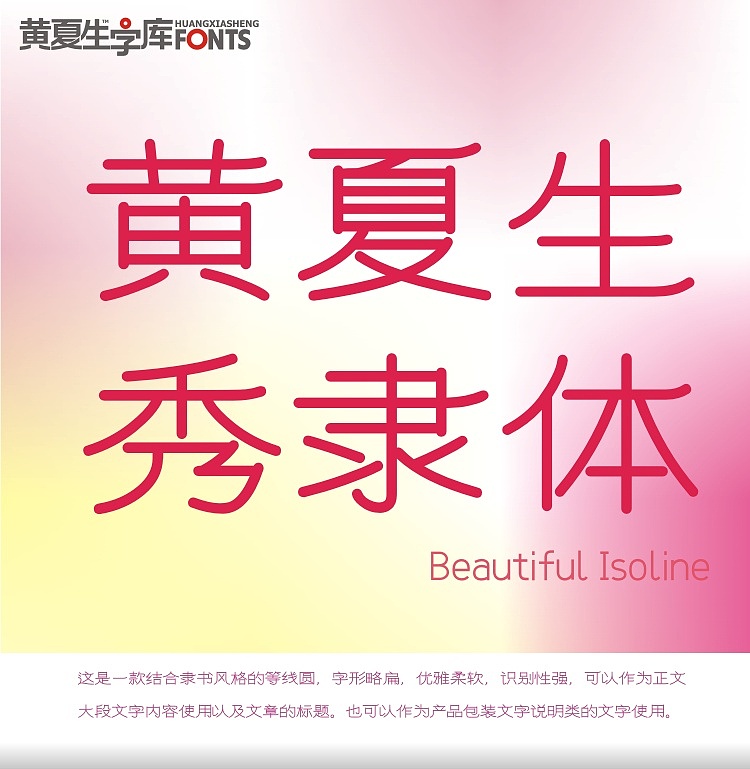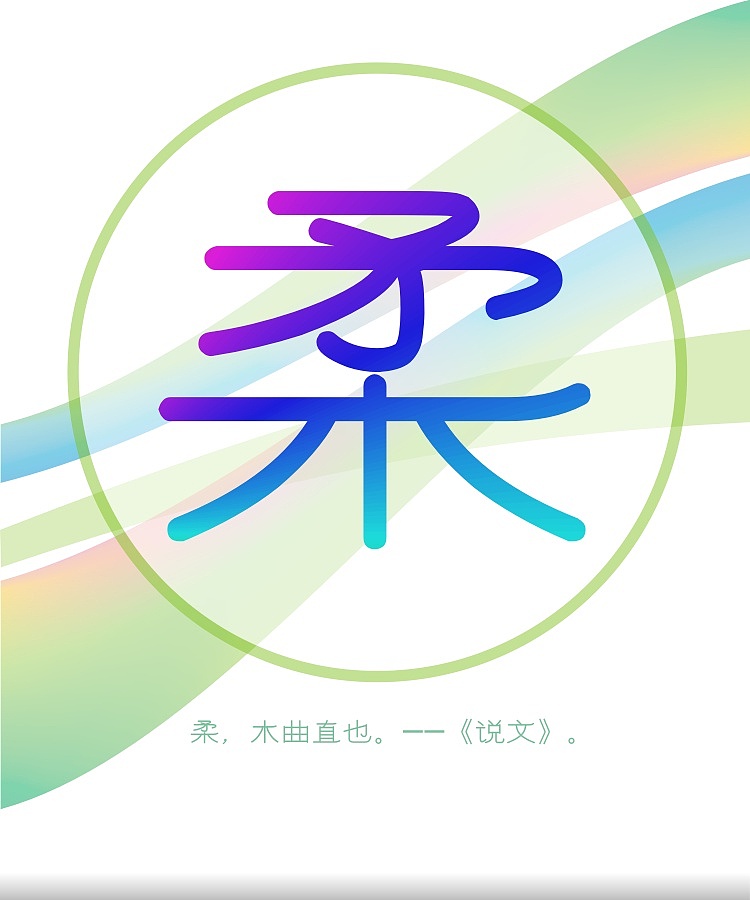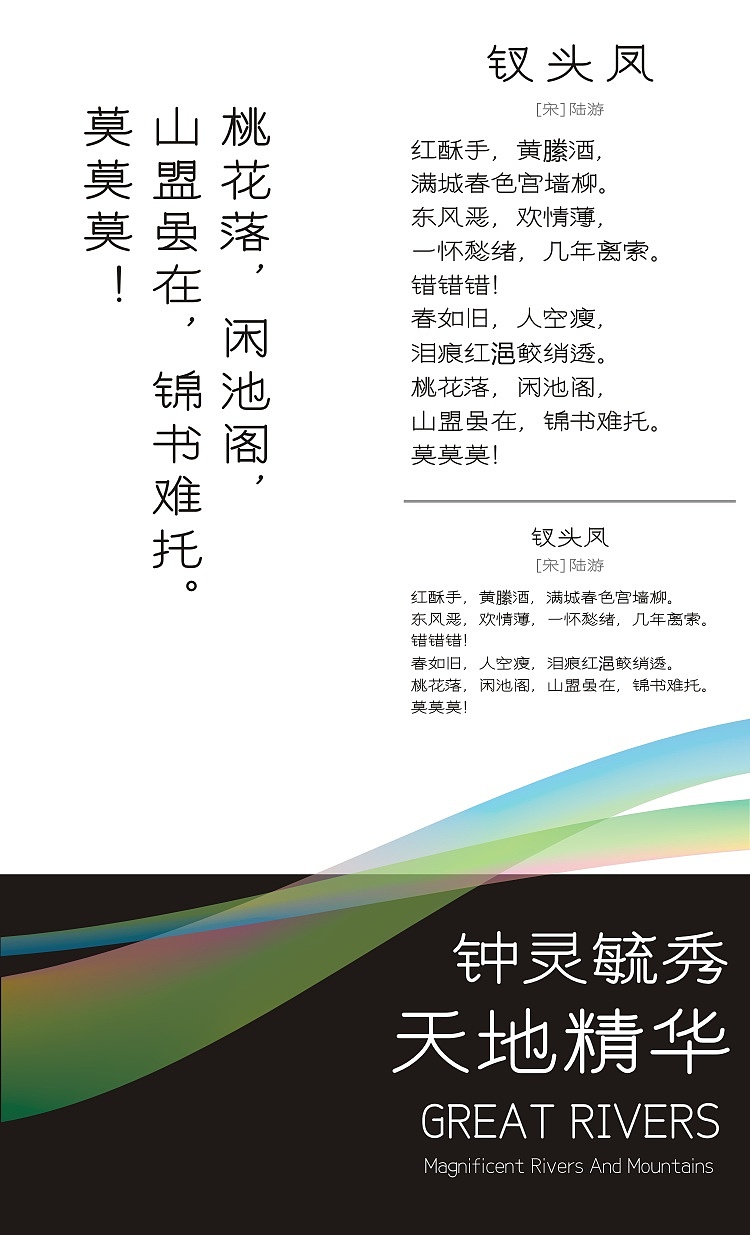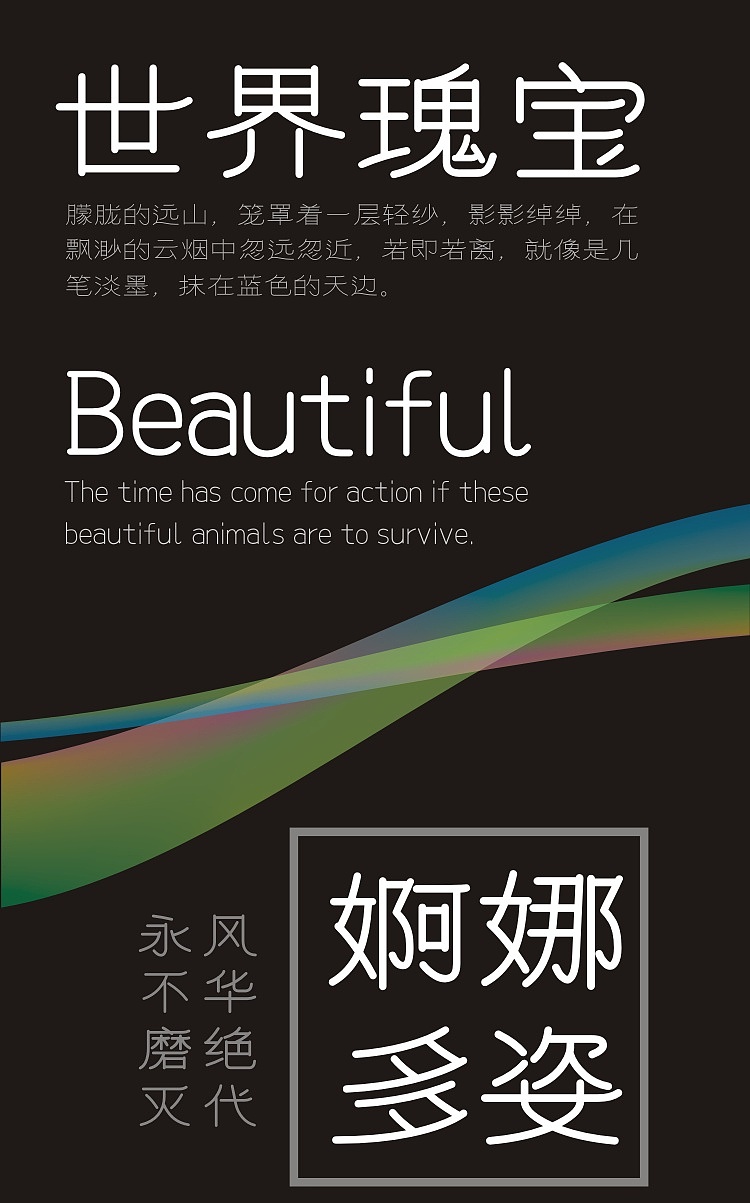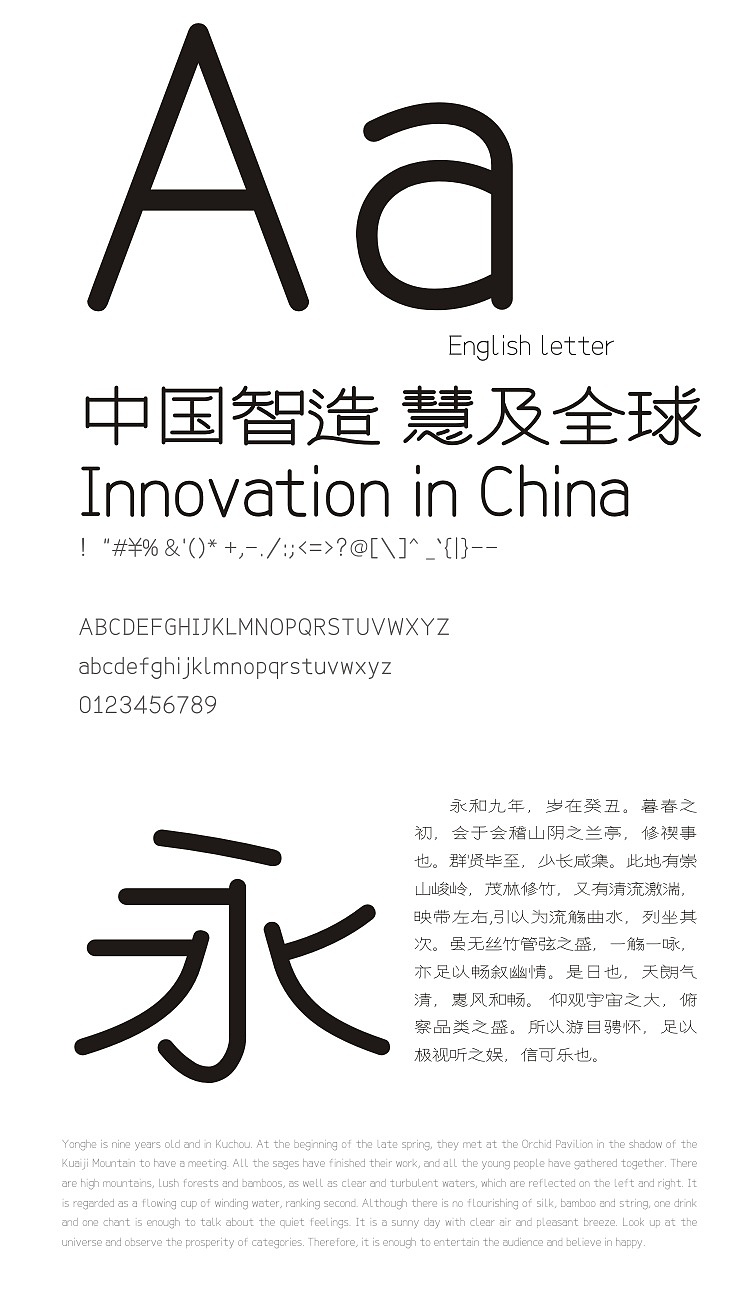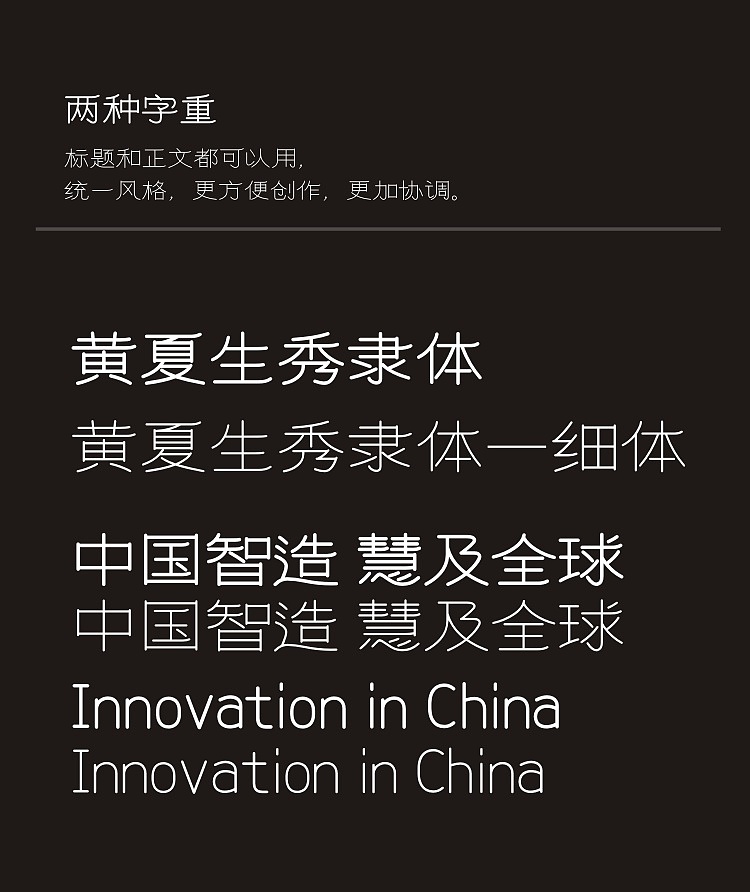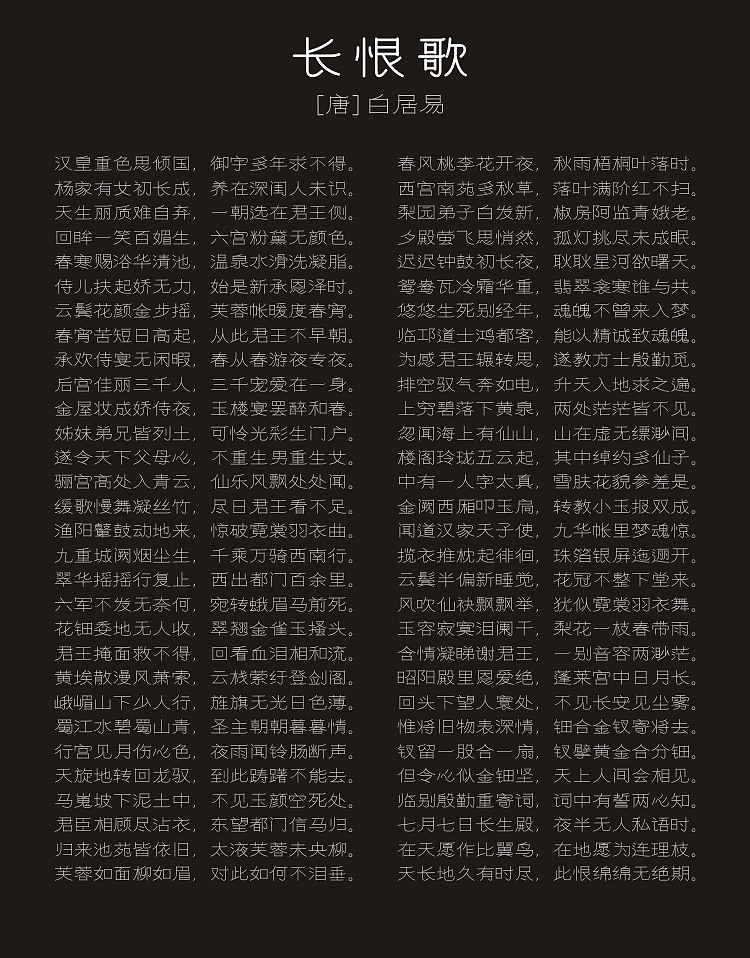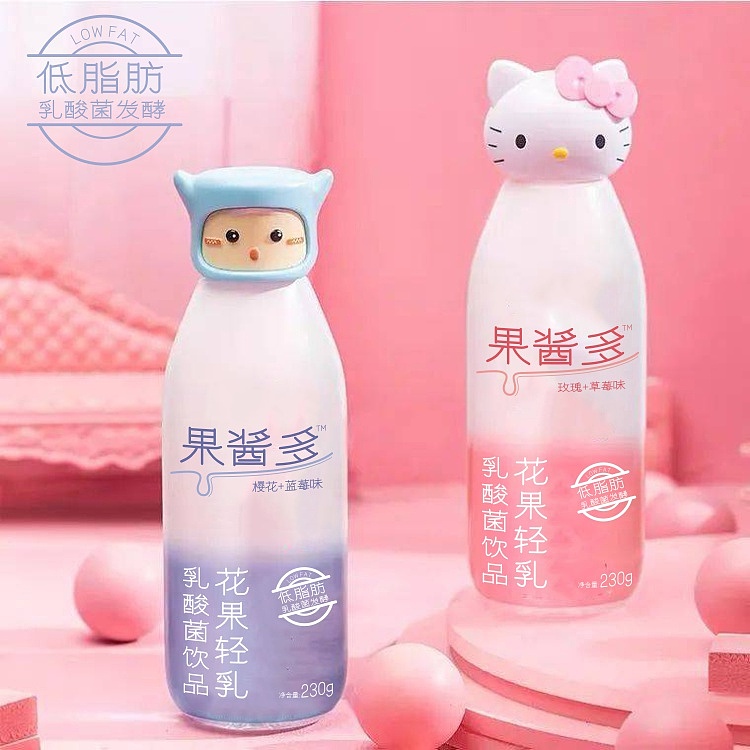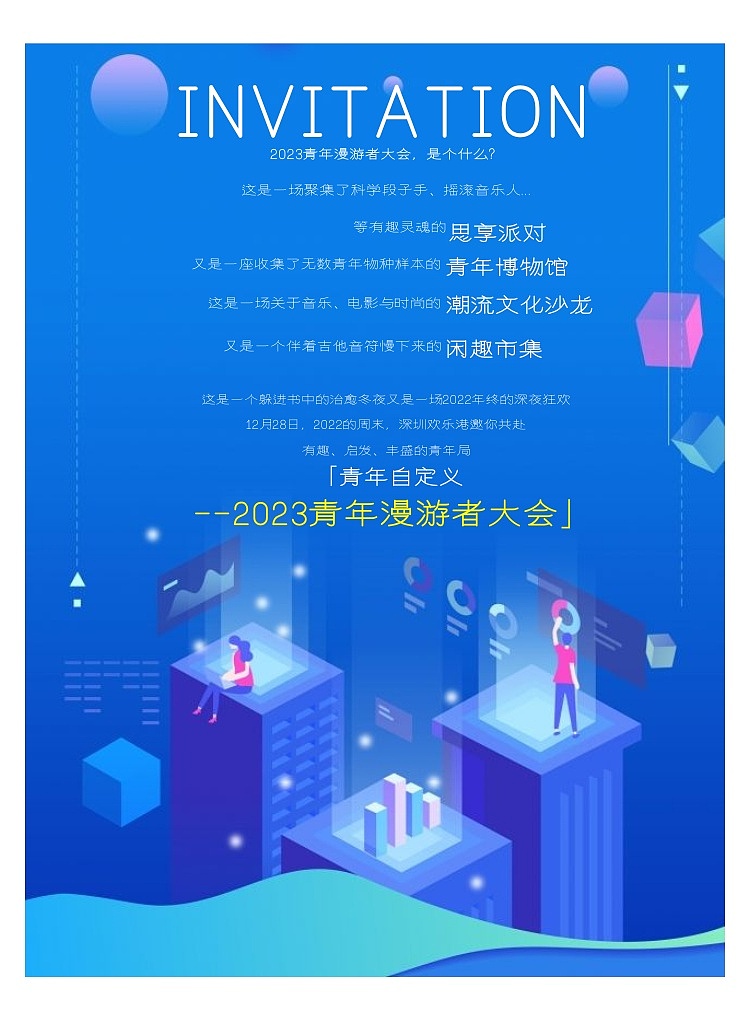
黄夏生秀隶体
五年了!只为一件事,是什么事情让我孤独的坚持了五年?那就是做字。
黄夏生直趣体这款字体,这是我设计的第三款字体,采用隶书结合圆体风格的等线体,字形略扁,优雅柔软,识别性强,可以作为正文大段文字内容使用以及文章的标题。也可以作为产品包装文字说明类的文字使用。尤其是女性类消费品包装和产品海报手册上特点显著。